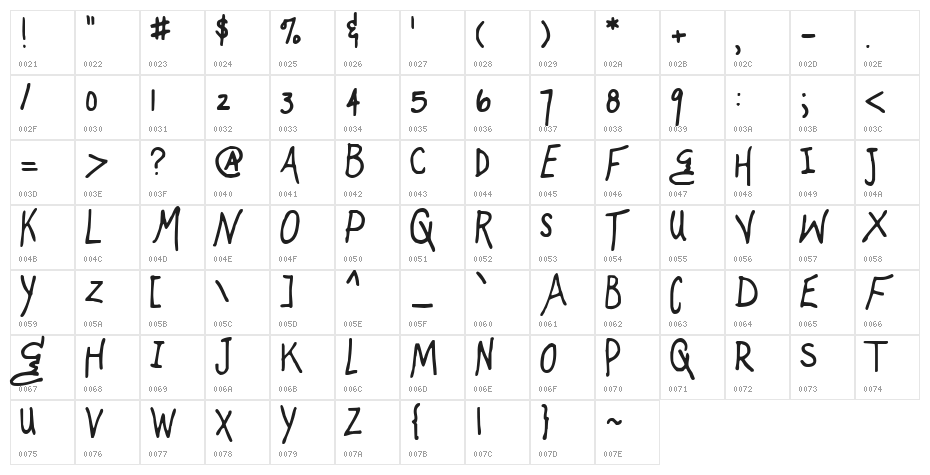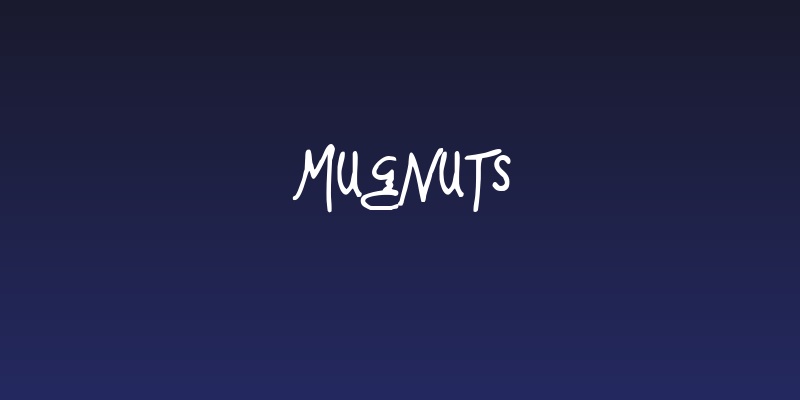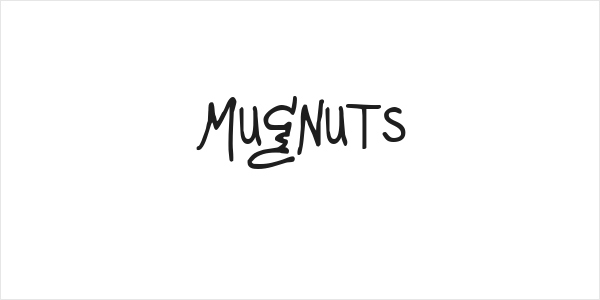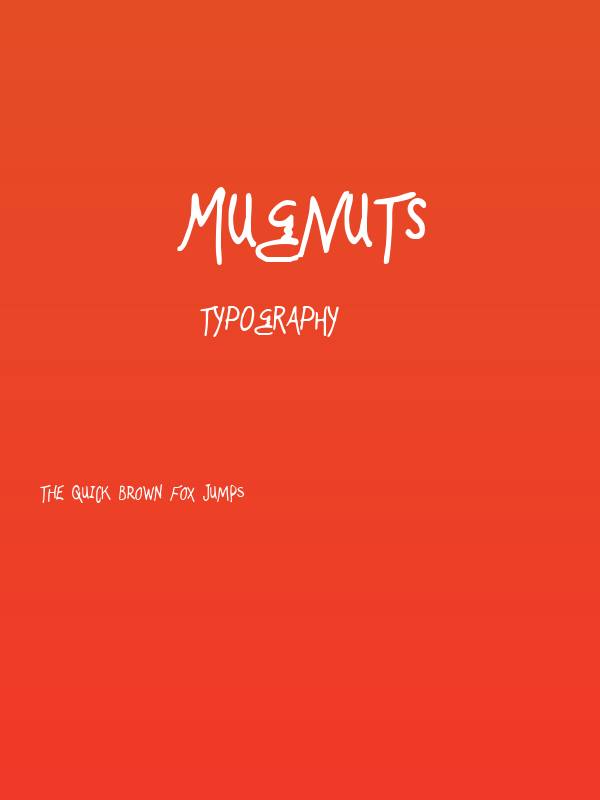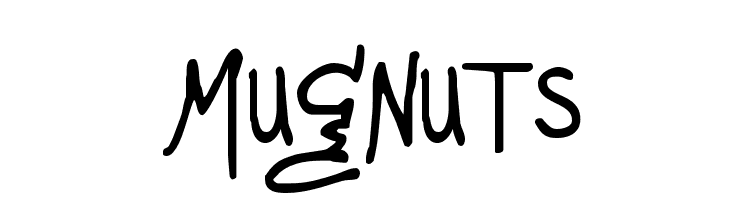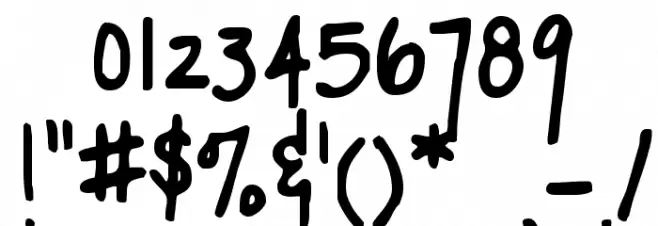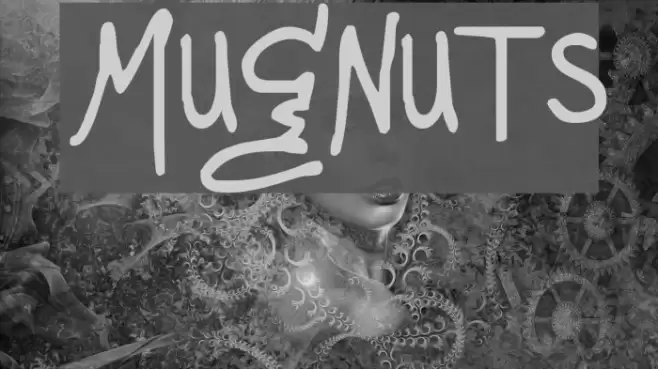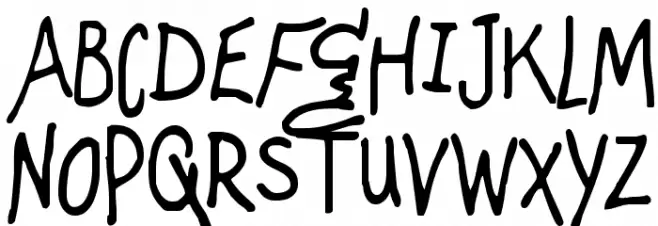
Mugnuts Font
| Общий стиль | Casual, Playful |
| Область применения | Headlines, Logos, Informal Text |
| Рекомендуемые проекты | Ideal for children's books, greeting cards, playful branding, and creative posters. |